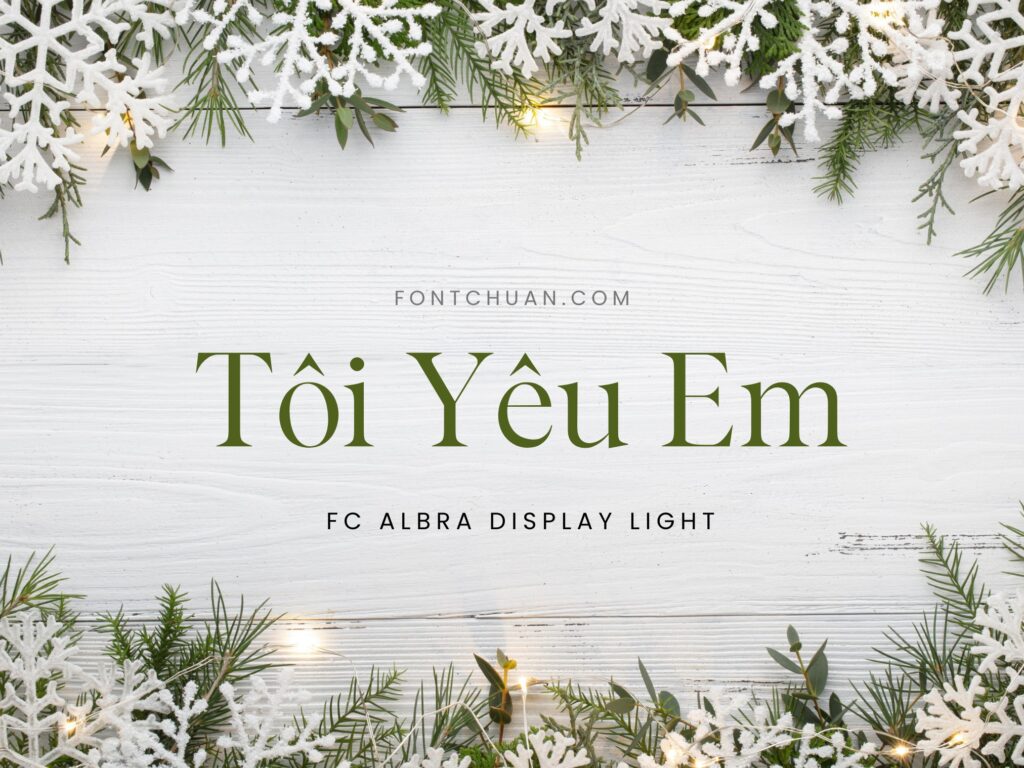
Font FC Albra Display Light Việt Hóa
Albra Display Light là một biến thể của họ font Albra, được thiết kế bởi Yang Lu và phát hành bởi BumbumType. Với thiết kế hình học hiện đại và đường nét tinh tế, Albra Display Light mang lại cảm giác thanh lịch và chuyên nghiệp, phù hợp cho các dự án thiết kế như thương hiệu, biên tập, bao bì và logo.
Khác với các bản font việt hóa khác thường mất phí, phiên bản Font FC Albra Display Light Việt Hóa do nhóm Font Chuẩn thực hiện và chia sẻ hoàn toàn miễn phí. FC Albra Display hỗ trợ đa ngôn ngữ, bao gồm các ký tự tiếng Việt đã việt hóa, tiếng Anh và nhiều ngôn ngữ Latin khác, mở rộng khả năng ứng dụng trong các dự án quốc tế.
Thành viên của Font Chuẩn đã chọn lọc và sưu tầm FC Albra Display Light, đáp ứng nhu cầu đa dạng của bạn đọc và hỗ trợ ứng dụng thực tế trong các dự án thiết kế. Với cấu trúc chữ cân đối, độ dày nhẹ và thiết kế tinh tế, Font FC Albra Display Light phù hợp cho các thiết kế yêu cầu sự sang trọng và hiện đại. Đặc biệt, trong các dịp mang tính tôn vinh và tri ân như Ngày Nhà giáo Việt Nam, Font ngày nhà giáo Việt Nam này lại là lựa chọn tuyệt vời nhờ nét chữ mềm mại, trang trọng, góp phần tạo nên những ấn phẩm truyền thông đầy ý nghĩa bên cạnh sự thanh lịch của Albra Display Light.